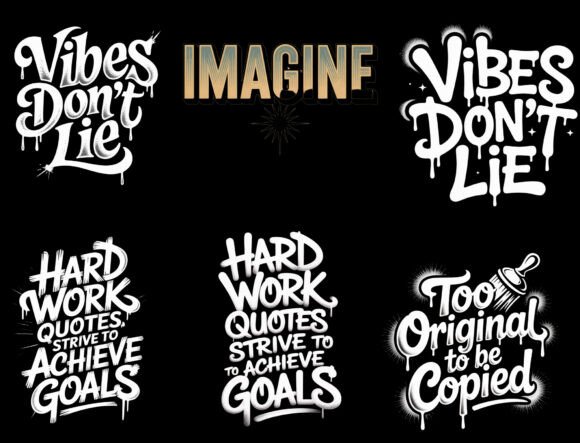
Retro Mood – Bold Vintage Font T-Shirt
Die richtigen Designelemente zu finden, kann eine Herausforderung sein, aber Retro Mood – Bold Vintage Font T-Shirt bietet eine außergewöhnliche Sammlung, die Ihre Arbeit sofort aufwertet.